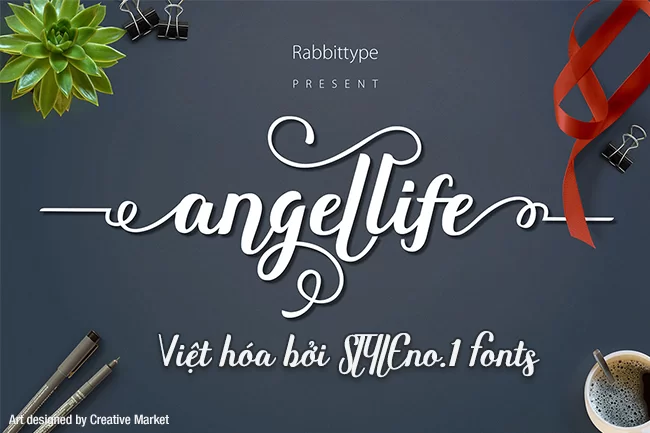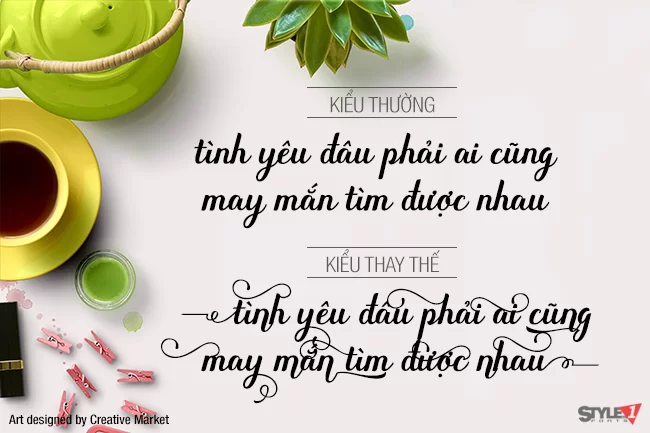
Font Việt hóa cực đẹp Angellife Beauty Script
Angellife là một Script đẹp, phù hợp cho thiệp mời đám cưới, thiệp chúc mừng, áo phông, logo hoặc bất kỳ thiết kế nào bạn tạo ra. Đi kèm với một bộ đầy đủ các ký tự chuẩn, ký tự thay thế, dấu câu, ký tự tượng hình quốc tế và ký tự thay thế theo phong cách.
Nhà thiết kế: Olexstudio
Nhà phát hành: Creative Market
Năm phát hành: 2016
Việt hóa: STYLEno.1 Fonts
Kiểu: Regular